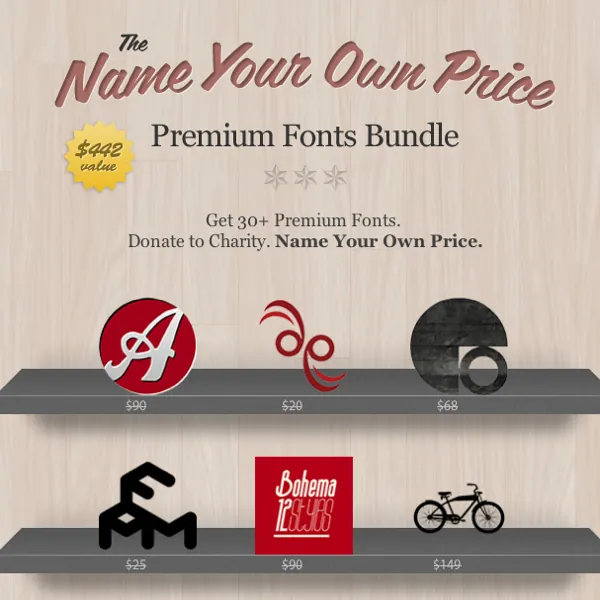
Torna il bundle con prezzo fai da te con il nuovo Stacksocial Premium Fonts Bundle. Questa volta in offerta ci sono 6 pacchetti di font professionali creati dai migliori esperti e designer di fonts. Chi è interessato all’acquisto può scegliere il prezzo da pagare, anche pochi centesimi di dollaro, per l’acquisto di 2 dei 6 pacchetti disponibili.
Stacksocial Premium Fonts Bundle propone in super sconto 6 pacchetti di fonts professionali, utilizzabili per qualsiasi progetto grafico o di design. I pacchetti in offerta includono Artist of Design Fonts con caratteri ispirati alle magliette dei college USA con inclusi anche caratteri distorti, Design Panoply Fonts Pack con fonts create a mano in stile retro, il pacchetto Fonts of Chaos Pack con fonts più moderne e stilizzate, BahnPro Family Font Pack con caratteri squadrati ispirati a scritte e cartelli storici dei mezzi pubblici austriaci, il pacchetto Bohema Family Font Pack con font in stile moderno e art deco infine il pacchetto Ashpole Fonts Pack con caratteri e anche immagini originali che possono essere utilizzati anche come icone.